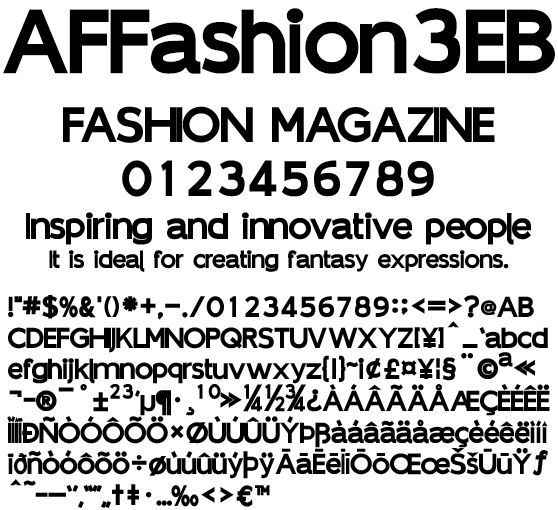
ファッション系 欧文ォント AFFashion3EB
AFFashion3EB
狭いサイドベアリングに強カーニングでファッション系に最適なEBウェイトサンセリフ欧文フォントです。ドキュメント、写真、動画テロップ、WebPage などにいかがでしょうか。パンフレット、リーフレット、フライヤー、ファッション系コンテンツに使えるフォントです。日本のローマ字表記で使われる訓令式やヘボン式で扱う Ô や Ō を収録、人名地名へのアプローチもリアルです。